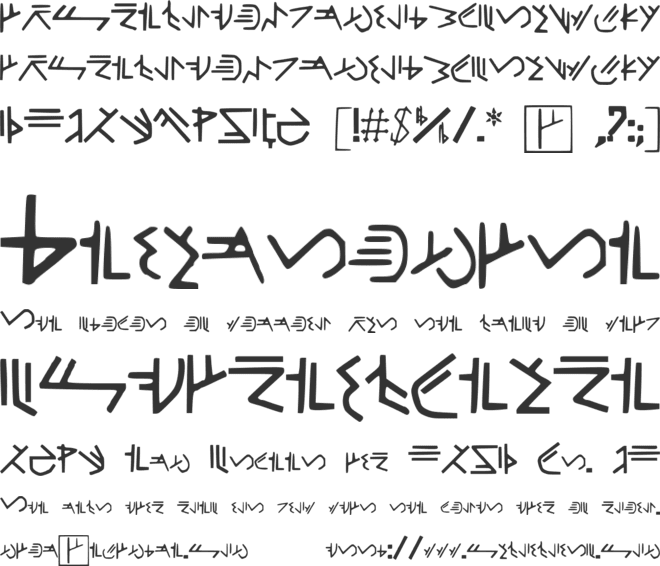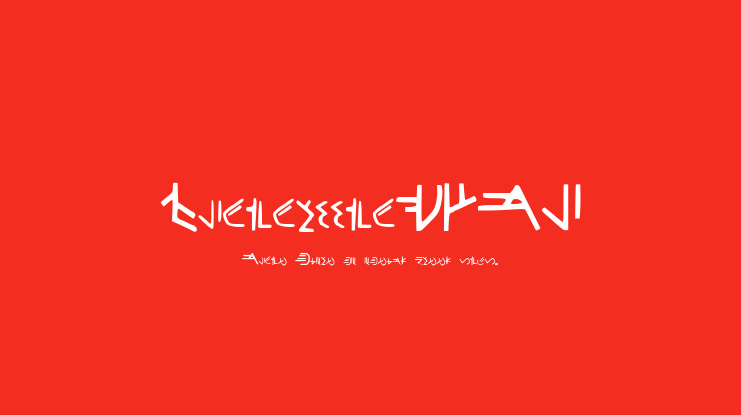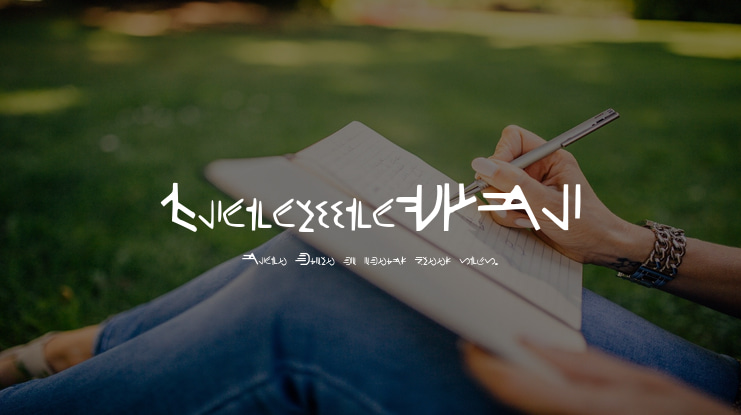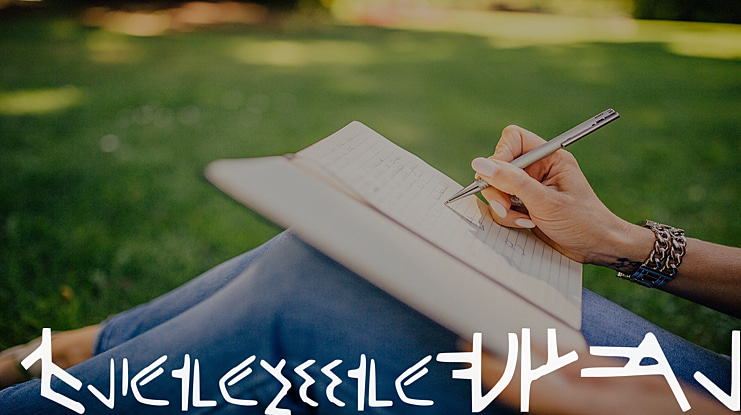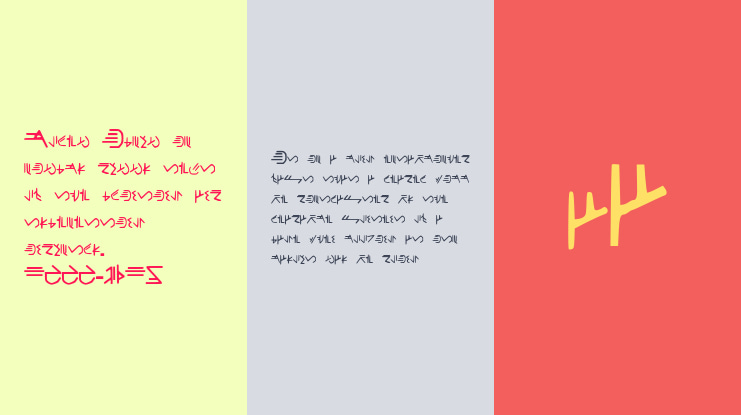
ForerunnerHALO Font
Esta es la fuente de la raza alien Forerunner de la saga de videojuegos "Halo". This is the font of the alien race Forerunner from the video game saga "Halo."